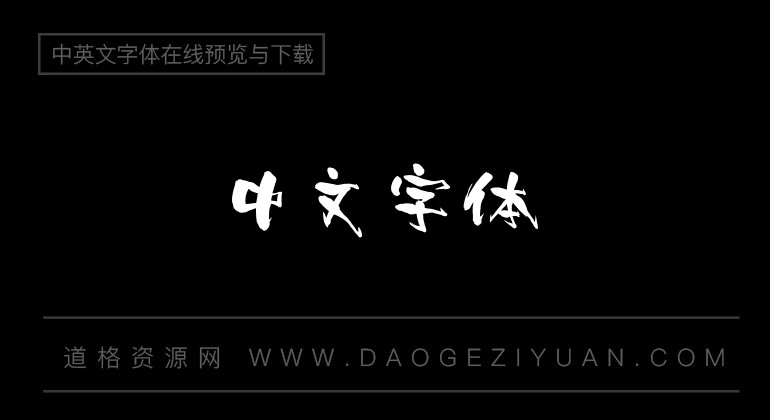
潮字社杨肖清书简
潮字社杨肖清书简是由杨肖清先生设计的一款字体,字体风格以清新、大气、潮流为主,具有浓郁的汉风气息,极具艺术性和现代感,适用于各种印刷、广告、招牌、网站设计等。字体的字形设计精细,笔画流畅,曲线优美,细节处理精致,极具视觉冲击力,为设计师提供了更多的创作空间。
潮字社杨肖清书简是一款非常不错的手写艺术字体,具有很好的视觉感,适合于文化类的宣传设计、商业类品牌的广告和产品包装设计以及个性化文字排版等较多场景。